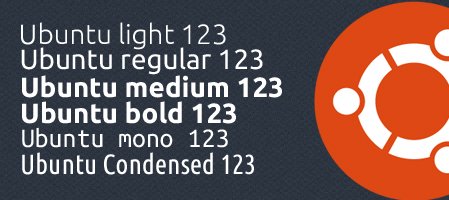
Ubuntu Font; Arriva Finalmente anche il Monospace!
Il team Canonical ha finalmente completato la famiglia dei Font Ubuntu rilasciando finalmente i nuovi font Ubuntu Monospace che vanno ad aggiungersi ai caratteri già disponibili
I nuovi font Ubuntu Monospace saranno sopratutto integrati per essere utilizzati sul nostro Terminale al posto del classico font Monospace utilizzato fin’ora, completando quindi il nostro desktop con tutti i font Ubuntu.
Ubuntu Monospace viene rilasciato in quattro varianti: Ubuntu Mono, Ubuntu Mono Bold, Ubuntu Mono Bold Italic e Ubuntu Mono Italic.
La famiglia Ubuntu Font Family è quindi completata avremo quindi Ubuntu light, Ubuntu regolar (quello che del logo per intenderci), Ubuntu medium, Ubuntu bold, Ubuntu mono e Ubuntu Condensed.